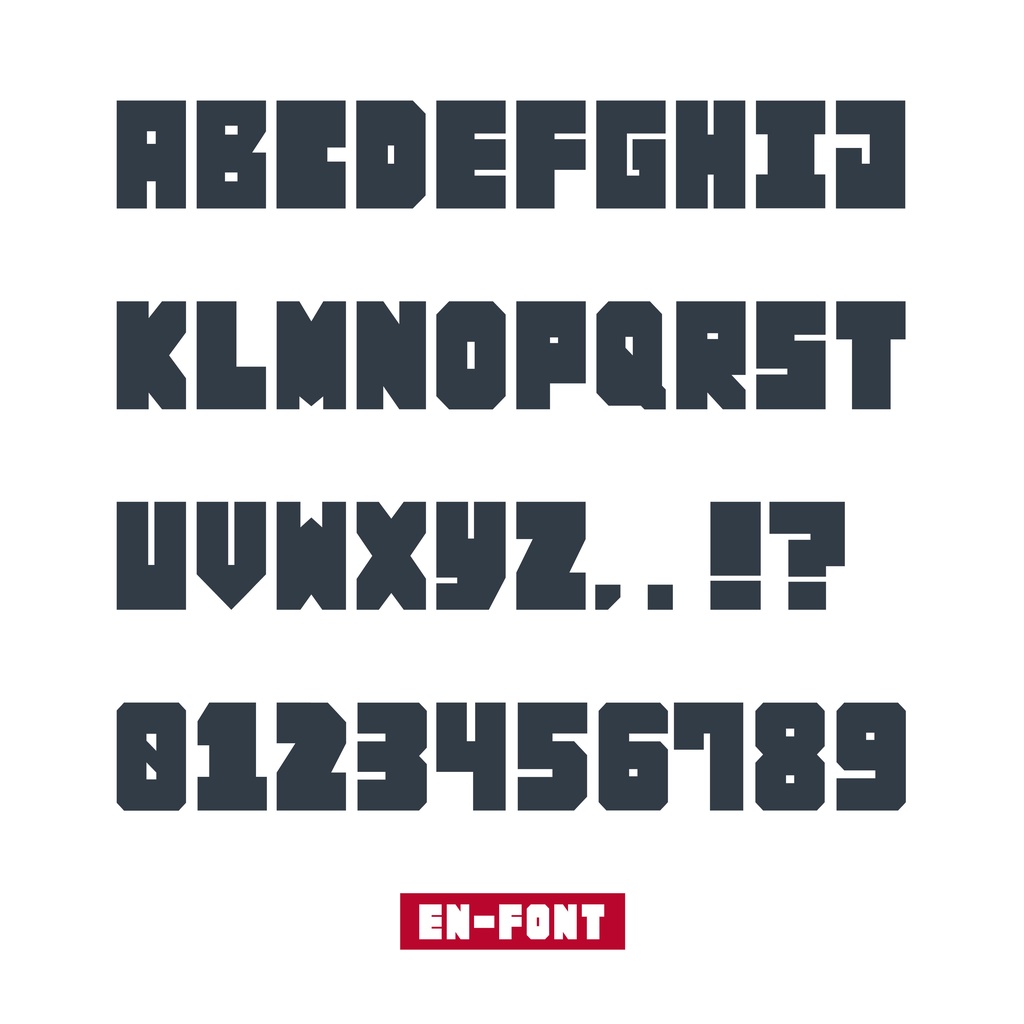
【フリーフォント】EN-FONT
【コンセプト】 長方形を削ったどっしりとしたパワフルな文字です。 スポーツやミリタリー、ゴツゴツとした荒っぽい格好よさ、また近未来的なデザインにマッチするようデザインしています。 ※現在大文字のみとなっております。 当フォントはイラスト・同人誌・動画・チラシなど、どの媒体でもご利用いただけます。 ご記載は任意ですが、ご利用の際は次のクレジットを入れていただけると嬉しいです! –––––––––––––––––––––––––––––– フリーフォント:EN-FONT ダウンロード:https://nkmr-umi.booth.pm/items/3675442 –––––––––––––––––––––––––––––– 【ご利用にあたって】 当フォントは無償でご利用いただけます。 デザインソフトやワープロなどのアプリケーションで自由にデザイン、印刷することが可能です。 個人利用・商用利用など使用範囲は問いません。 変形などもご自由になさってください。 【禁止事項】 インストール、ご利用にあたり下記の事項をお守りいただきますようお願い致します。 ・有償、無償に問わず再配布禁止。 ・公序良俗に違反している制作物への利用禁止。 (ヘイトスピーチや著しく偏った思想、暴力、著作権の侵害など違法行為の助長を促すものなど) 当フォントをインストールした時点で上記に同意するものとします。 同意いただけない場合、当フォントを利用することはできません。